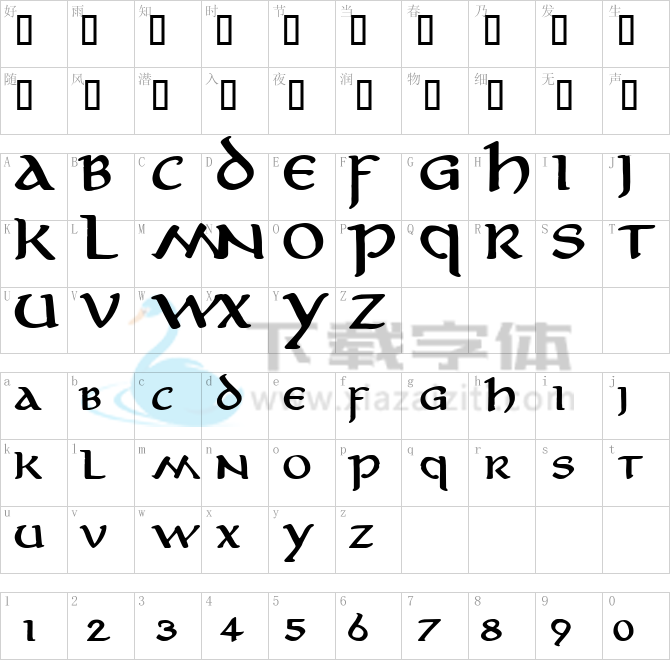
Aniron.ttf字体下载,这款字体结构工整、笔画清晰,兼顾美观与易读性,适用于标题、正文、海报、包装、LOGO 等多种场景。字形优雅稳定,风格百搭耐看,适配日常排版与创意设计,让文字呈现更舒适、更具质感。Aniron.ttf字体下载一笔一画,皆是细节,以均衡的比例、流畅的线条打造舒适视觉体验,字形端正大气,风格简约现代。无论是商业设计、品牌宣传还是日常排版,都能轻松驾驭,让文字更有格调与力量。Aniron.ttf字体下载字体下载。